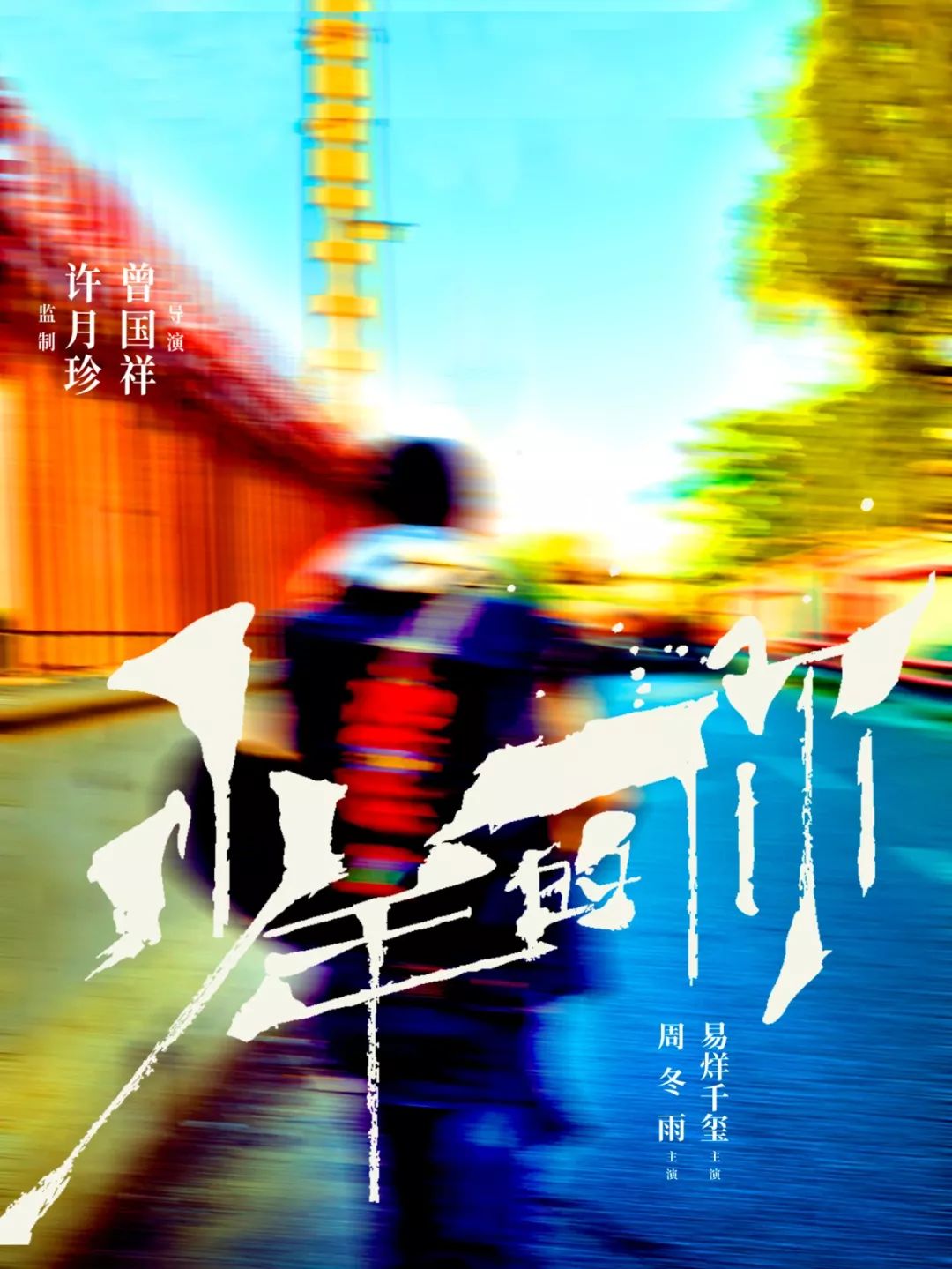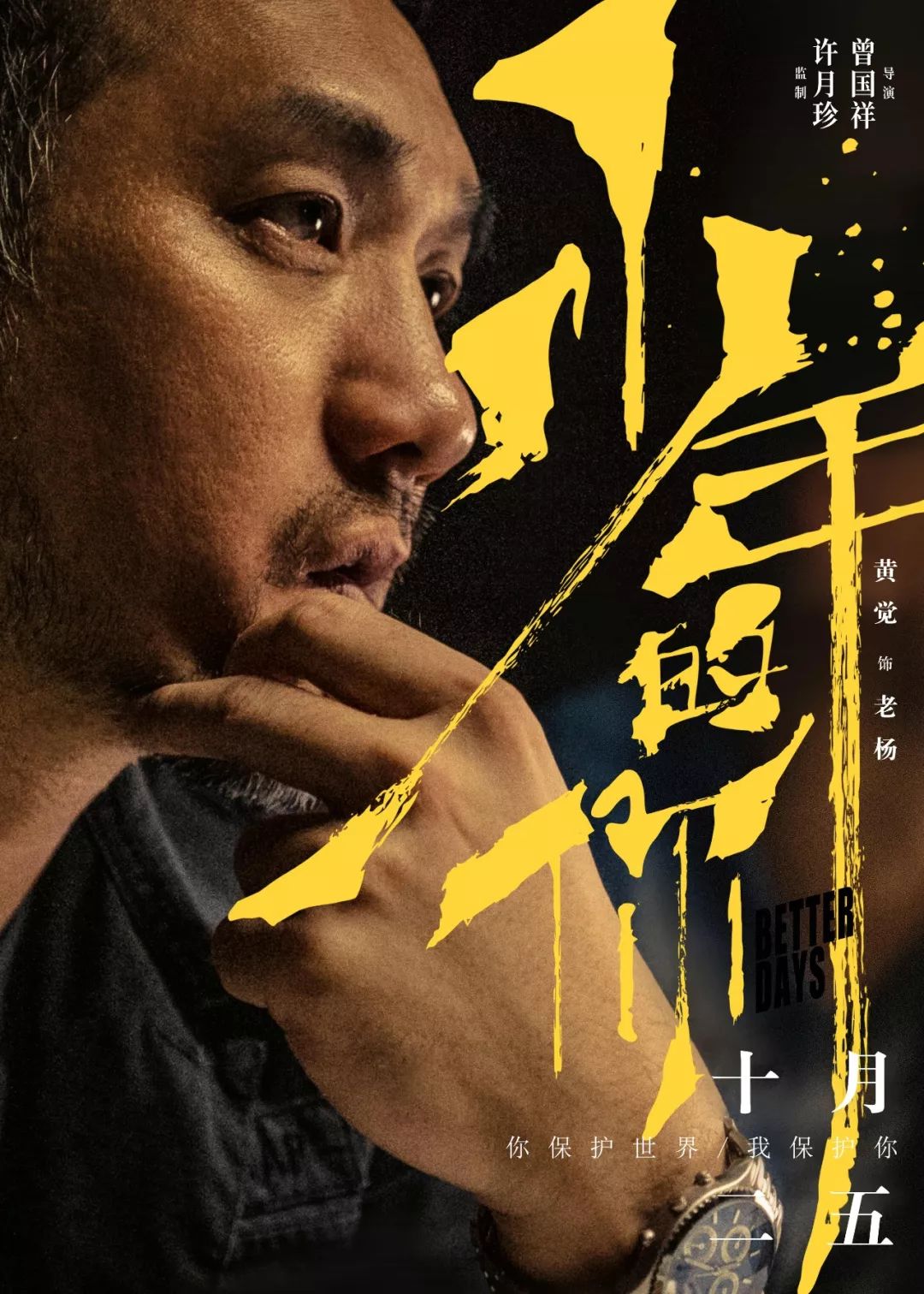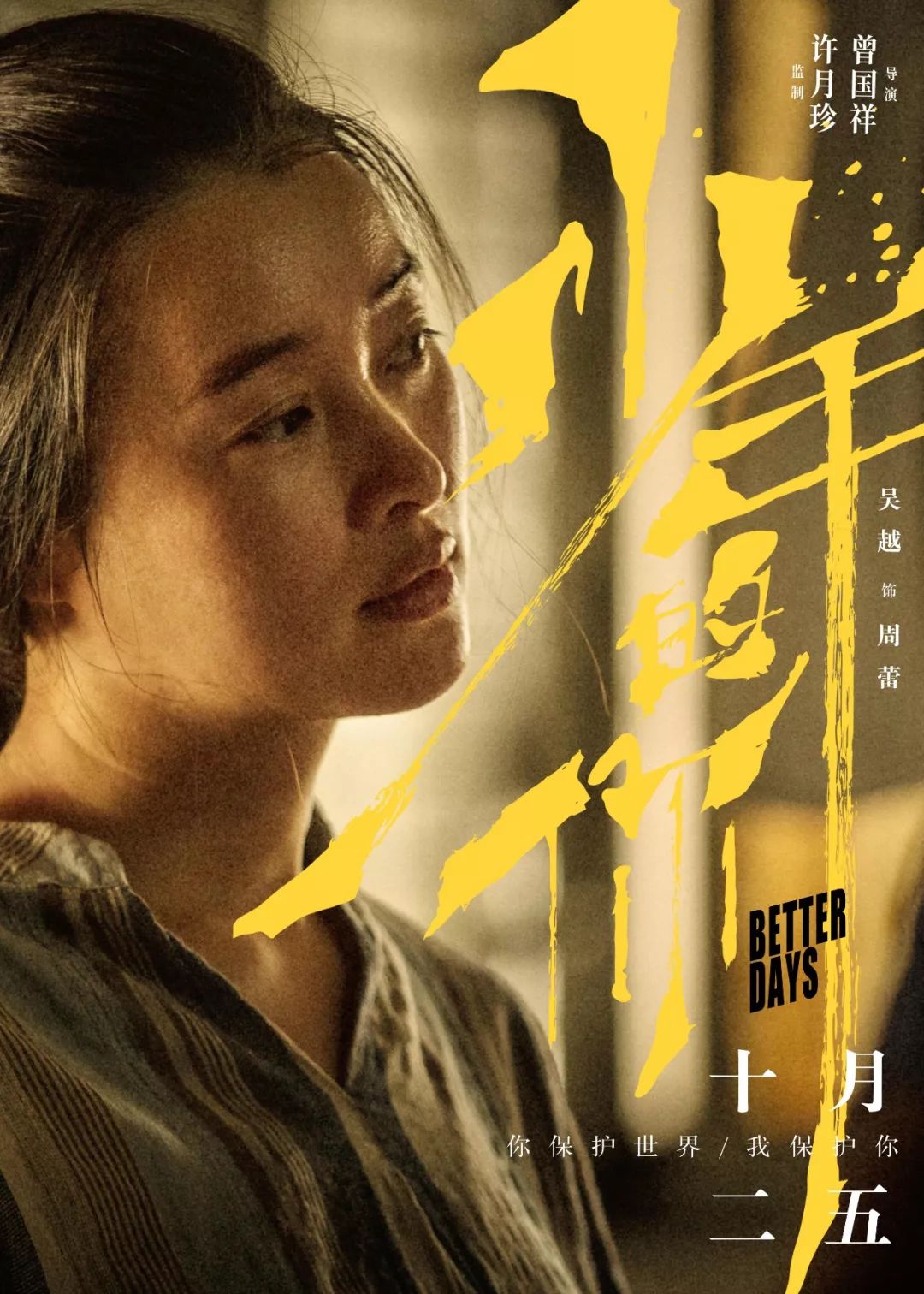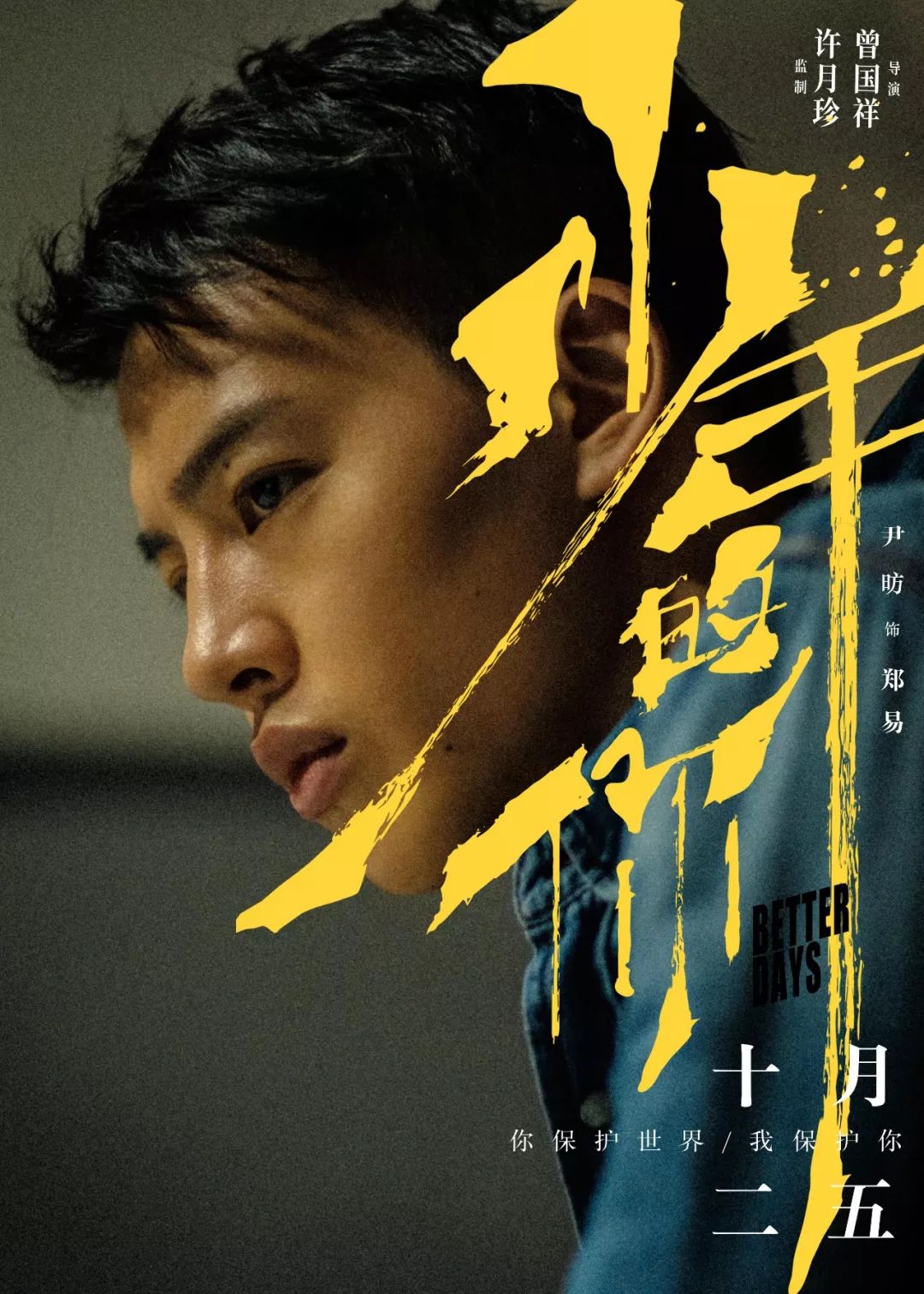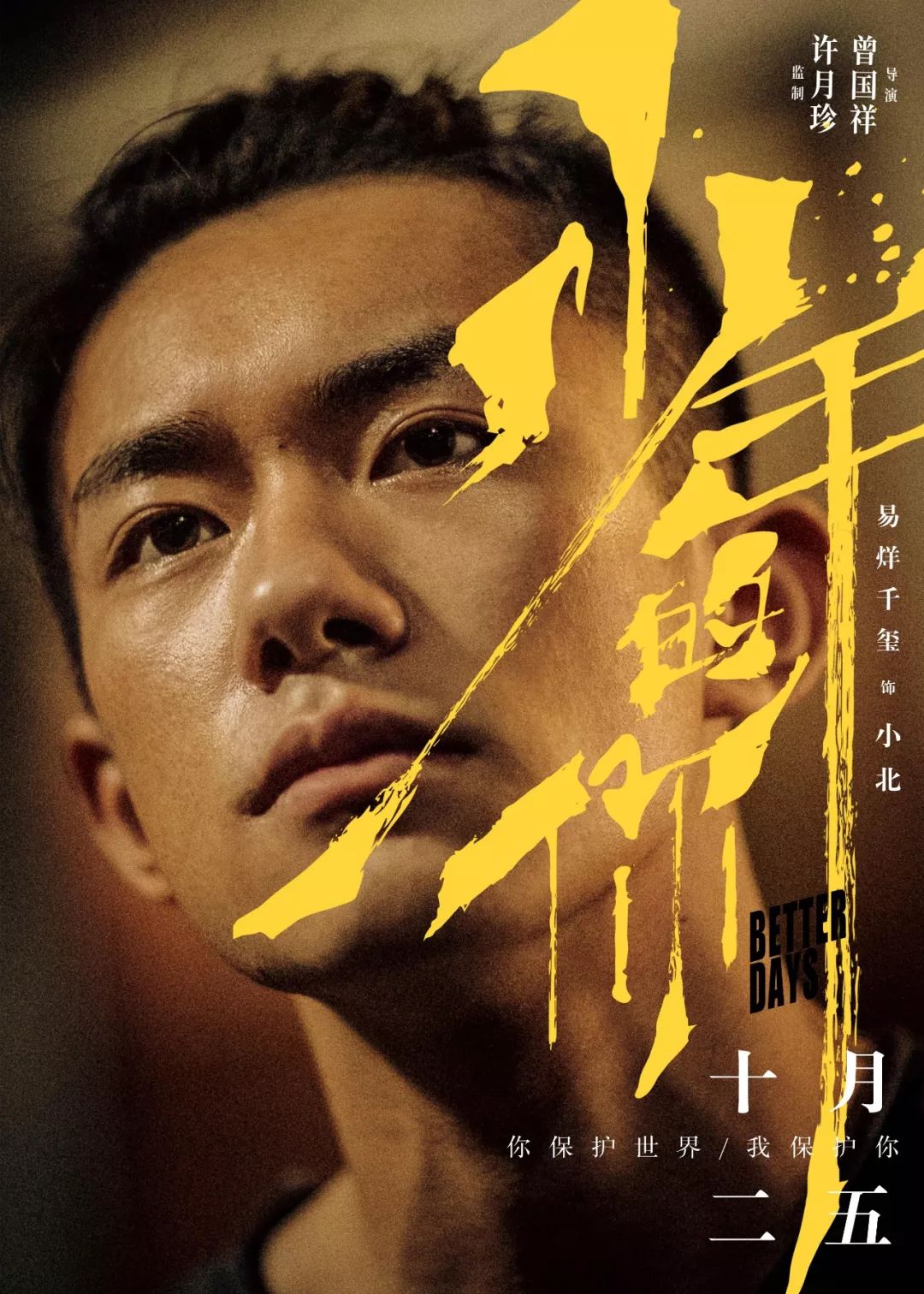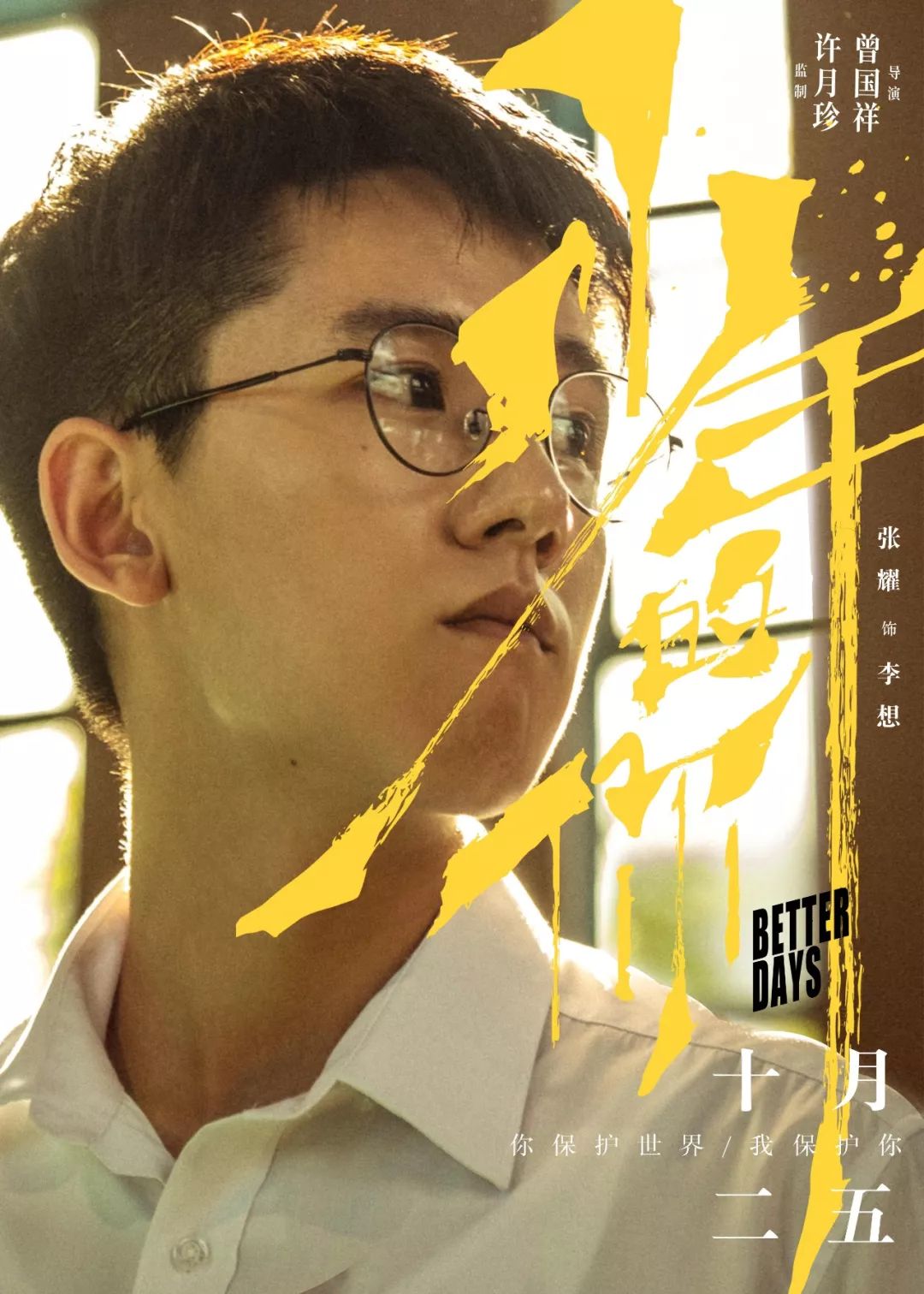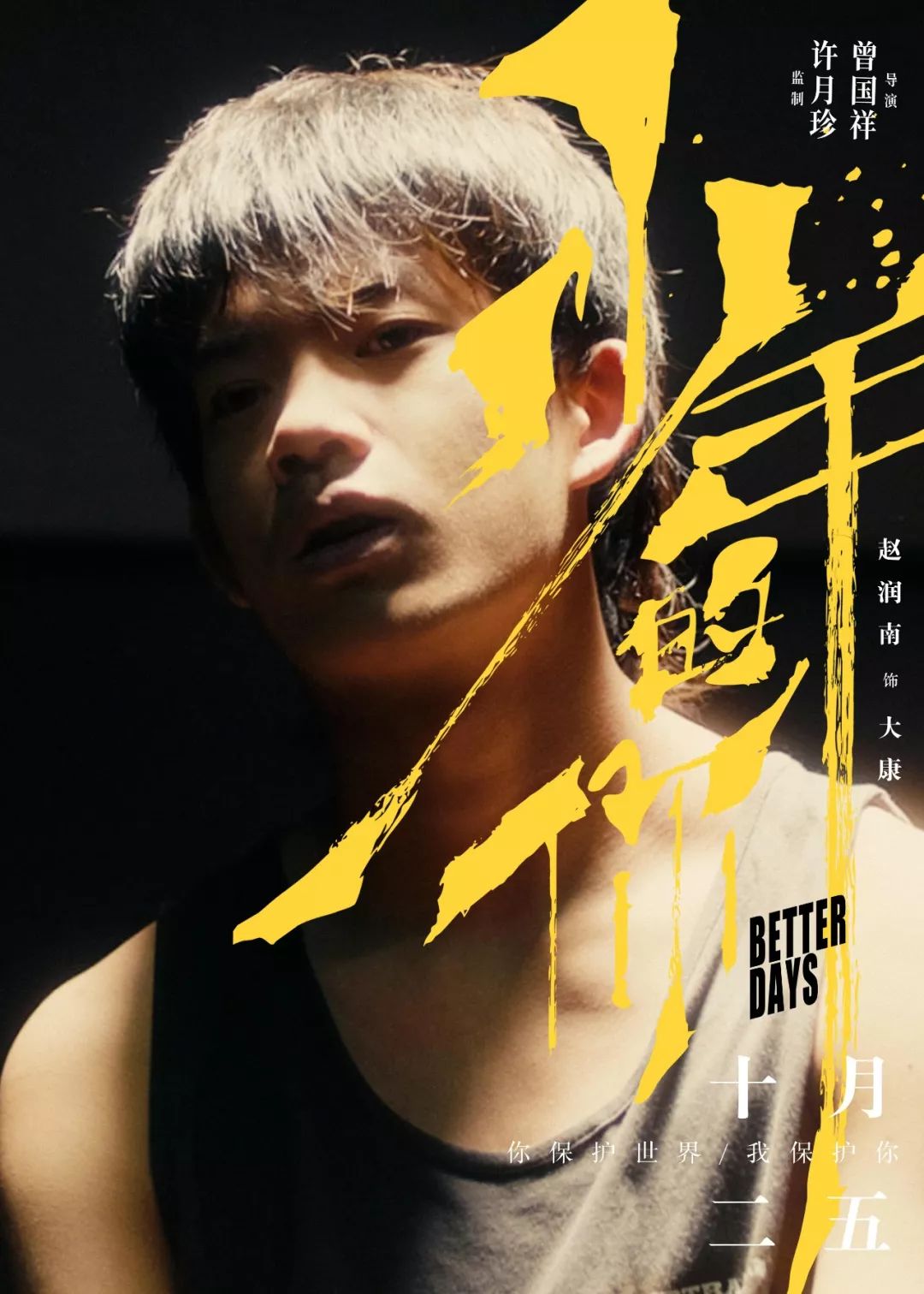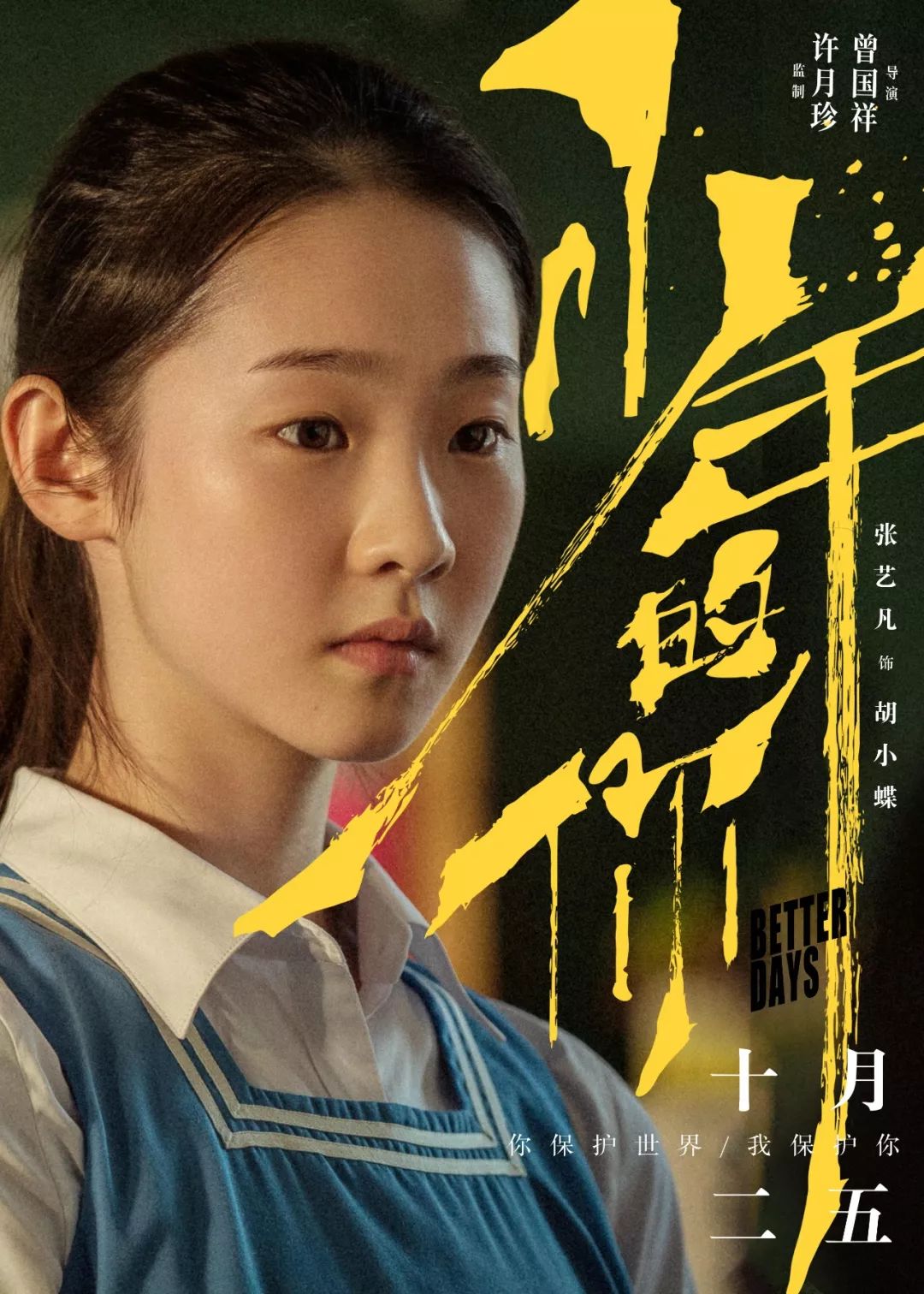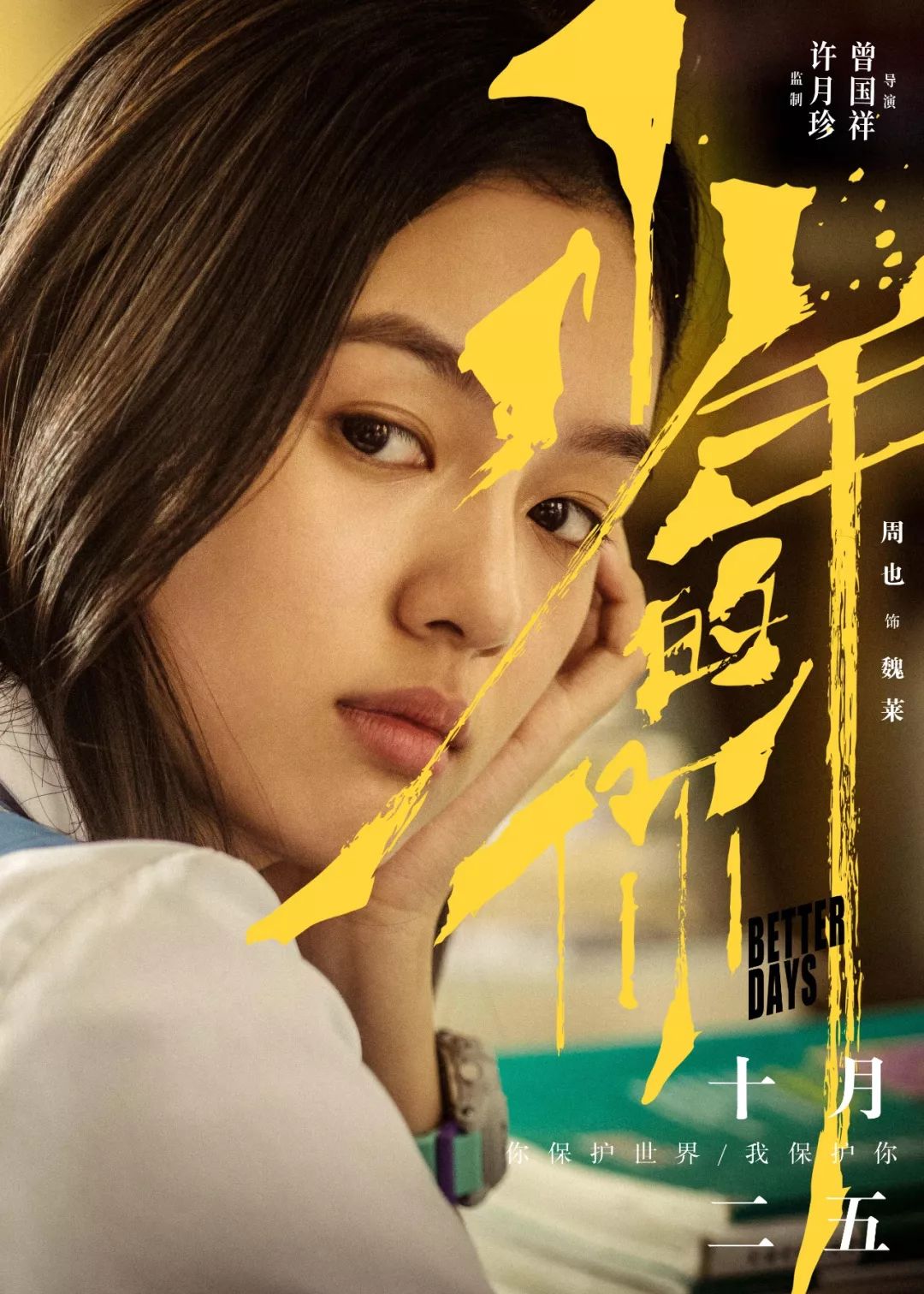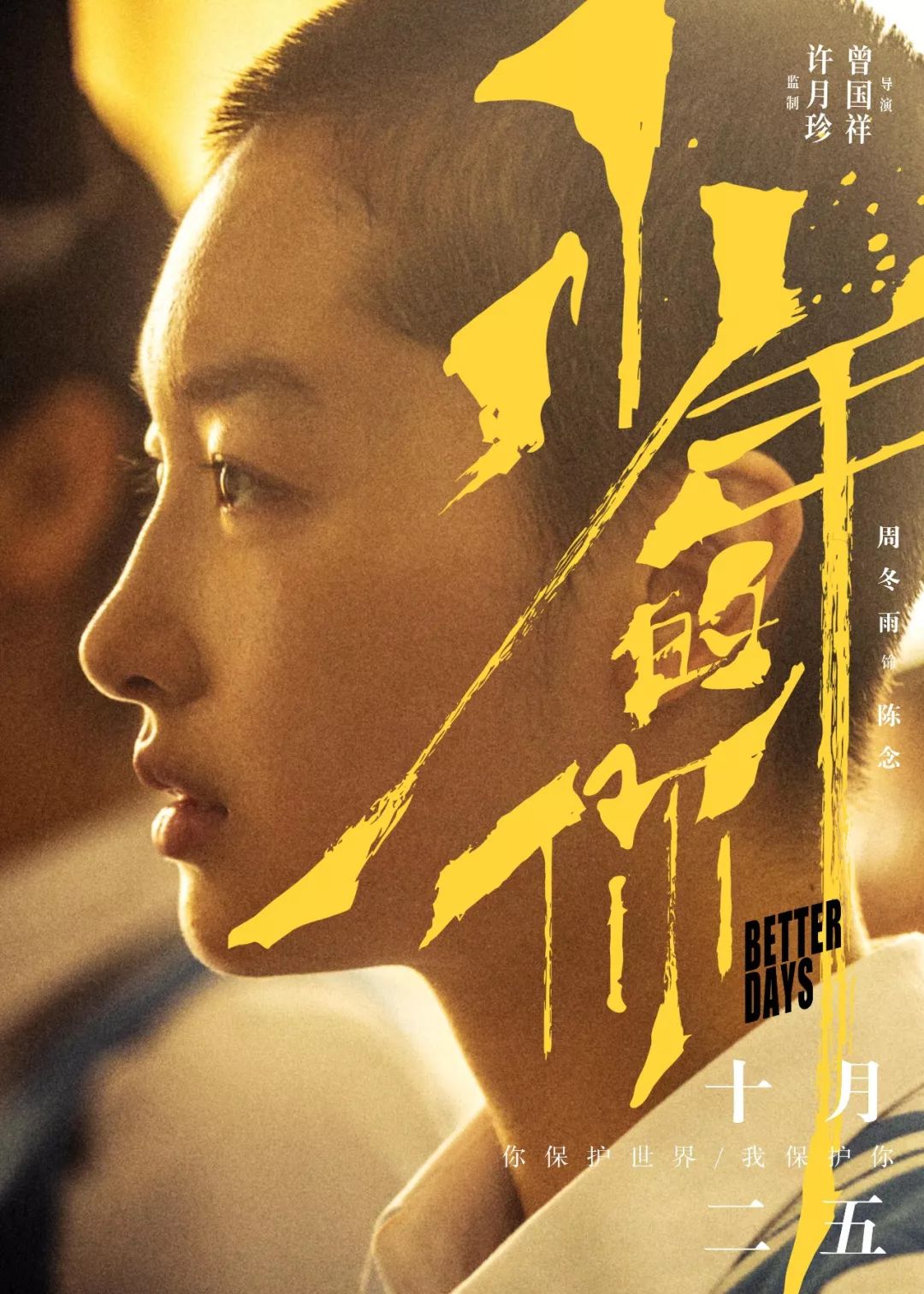
《少年的你》火的不止是电影,还有那不屈的字体
不过这都没有电影中的惨,还记得这个预告海报吗?
就在上周五,经历撤档风波又突然定档的《少年的你》,口碑票房双爆!
可柚子职业素养加身,最关心的还是这个几乎占了整个海报C位的字体。
果然还是无悬念的黄海,又能设计海报,又能设计字体,真的是优秀本尊了。
仔细看,你会发现这是书法体,笔画有粗有细,对比鲜明,反映出主角的倔强、无畏的性格特征。
拉长的笔触,给人一种年少轻狂的拼劲,算是情绪很丰富的一款字体设计了。
除了电影海报,官微还在高考前夕发布了超燃文案宣传海报,以思源宋体一个横排、一个纵排,传达了人物的潜台词,让人仿佛“嗅”到了自己的青春。
主题曲《我们很好》发布时,也做了一系列歌词图片,虽是简单的手写体,却能通过文字,感受到那故事背后,倾诉出的孤独和无助……
连观众的真实观后感,也不放过,做成了文案宣传图,看着就好哭~
最后我想说,情感永远是最能深入人心的东西,而它的载体除了文字,还有字体。